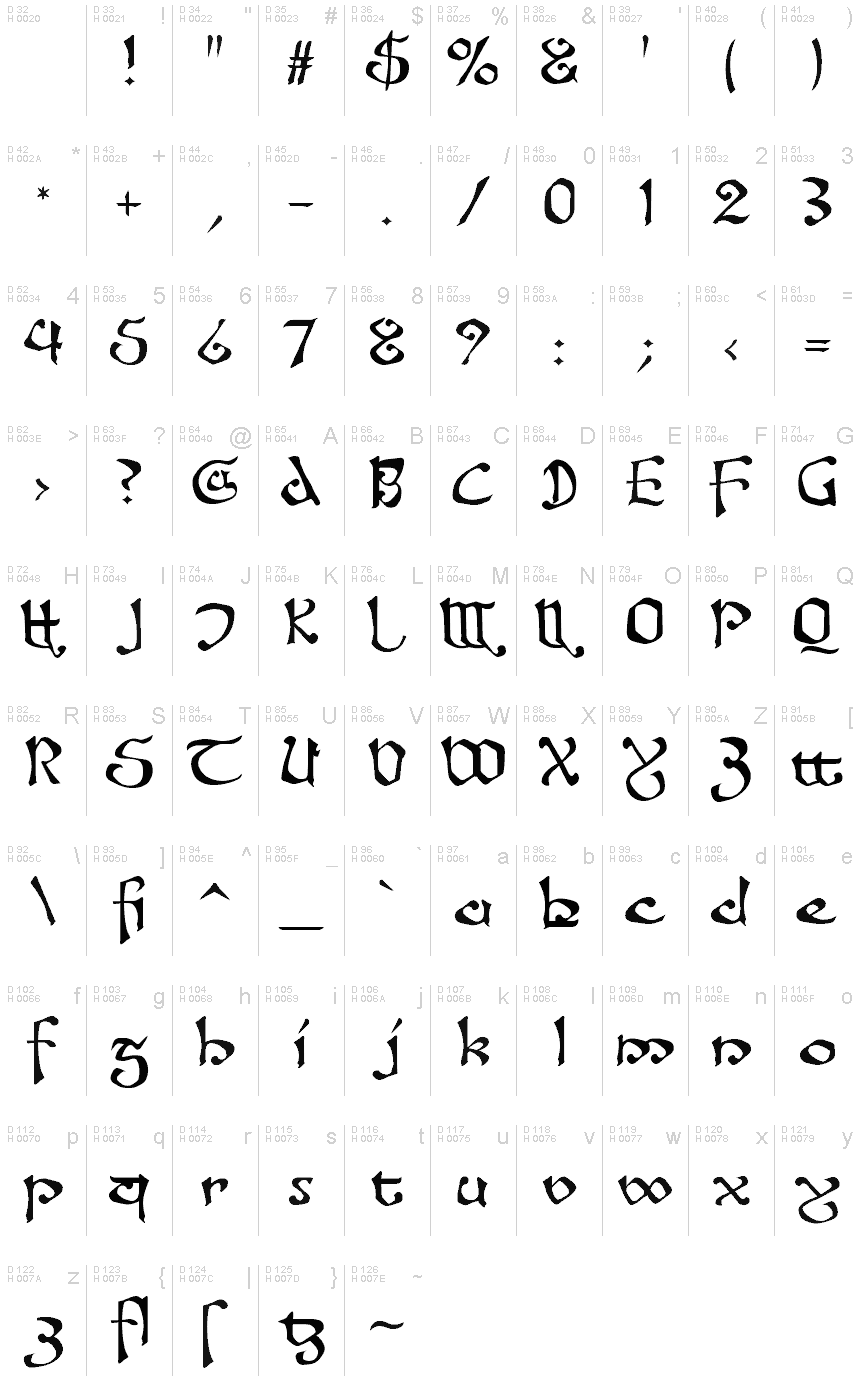
Fanjofey AH von Fontgrube Andreas Höfeld ist eine kostenlose Retro-Display-Schrift mit einer wunderbar eigentümlichen, tintigen Ausstrahlung. Mit ihren krummen Stämmen, ausgestellten Strichen und verspielten, unebenen Kurven wirkt sie wie von Hand auf Pergament für ein Märchen oder eine Fantasy-Karte gezeichnet. Die Buchstaben scheinen zu wackeln und zu tanzen, was Überschriften einen handgefertigten Storybook-Charme verleiht, den saubere digitale Schriften nur schwer imitieren können.
Mit Fanjofey AH verleihst du Fantasy-Buchtiteln, RPG-Überschriften, Einladungen für Mottopartys, Postern, Gaming-Logos und YouTube-Thumbnails einen einzigartigen Charakter. Diese kostenlose Schrift glänzt vor allem in großen Größen, wo ihre eigenwilligen Silhouetten zur Geltung kommen; kombiniere sie für den Fließtext mit einer schlichten geometrischen Sans-Serif, um ein ausgewogenes und lesbares Schriftbild zu erhalten.
Fanjofey AH
Andreas Höfeld
This typeface is for all fans of "Lord of the Rings", the literary classic by R.R. Tolkien, recently popular through the LOTR and Hobbit trilogies. For his fictional world "Middle Earth" Tolkien designed the "Tengwar" alphabet. Supposedly the writing of the Elves, Tolkien also used it to write the languages (invented by himself) of other races in Middle Earth.
Fanjofey is a latin alphabet - using many traits of the Tengwar letters, thus giving your texts a "Lord-of-the-Rings" look and feel. Some of the vowel signs above and below the letters are added in the companion typeface "Fanjofey Leoda", enhancing the "Elvish" feeling.